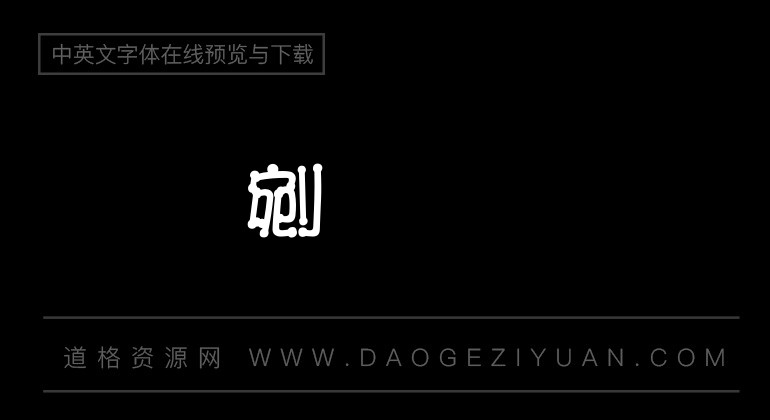
文鼎火柴体
文鼎火柴体是一款基于毛笔书法的中文字体,由香港著名字体设计师黄伟汉先生设计,于2006年发布。文鼎火柴体以火柴棍做为笔触,以毛笔书法的手法书写中文字体,融合了传统书法的精髓,拥有传统书法的灵动感和活力,更具有亲和力和艺术感。文鼎火柴体让毛笔书法的精髓走入了现代时代,更加活泼,它可以满足不同的设计需求,适合用于各种印刷品、网页和电子媒体的中文字体设计。
文鼎火柴体是一款非常不错的手写艺术字体,具有很好的视觉感,适合于文化类的宣传设计、商业类品牌的广告和产品包装设计以及个性化文字排版等较多场景。